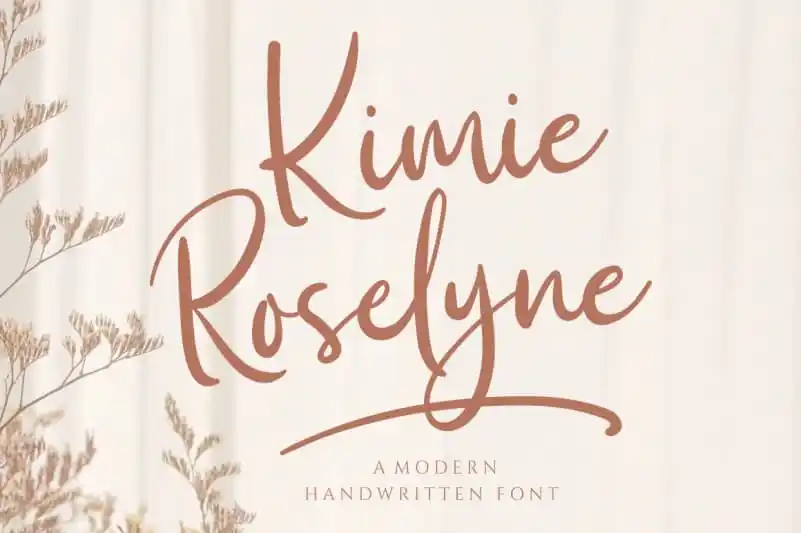
Kimie Roselyne Script Font – Download Grátis
A nova fonte de script elegante moderna “Kimie Roselyne Script Font” é ideal para designers que buscam adicionar um toque sofisticado a suas criações digitais. Com aparência irresistivelmente moderna e fluida, esta fonte será uma escolha perfeita para estilos de logotipos, materiais de marca, cartões de convidados, embalagens de eventos, além dos layouts do Facebook, Instagram e outras plataformas sociais. O design fluido da “Kimie Roselyne Script Font” irá garantir que seu trabalho tenha um visual atraente, sem deixar de lado as características distintivas do estilo script. Não importa o projeto – esta fonte trará ao seu design uma sofisticação e elegância únicas. Seja você um designer gráfico, editor de fotos ou até mesmo um escritor, “Kimie Roselyne Script Font” será sua melhor aliada para criar trabalhos incríveis com uma aparição única.